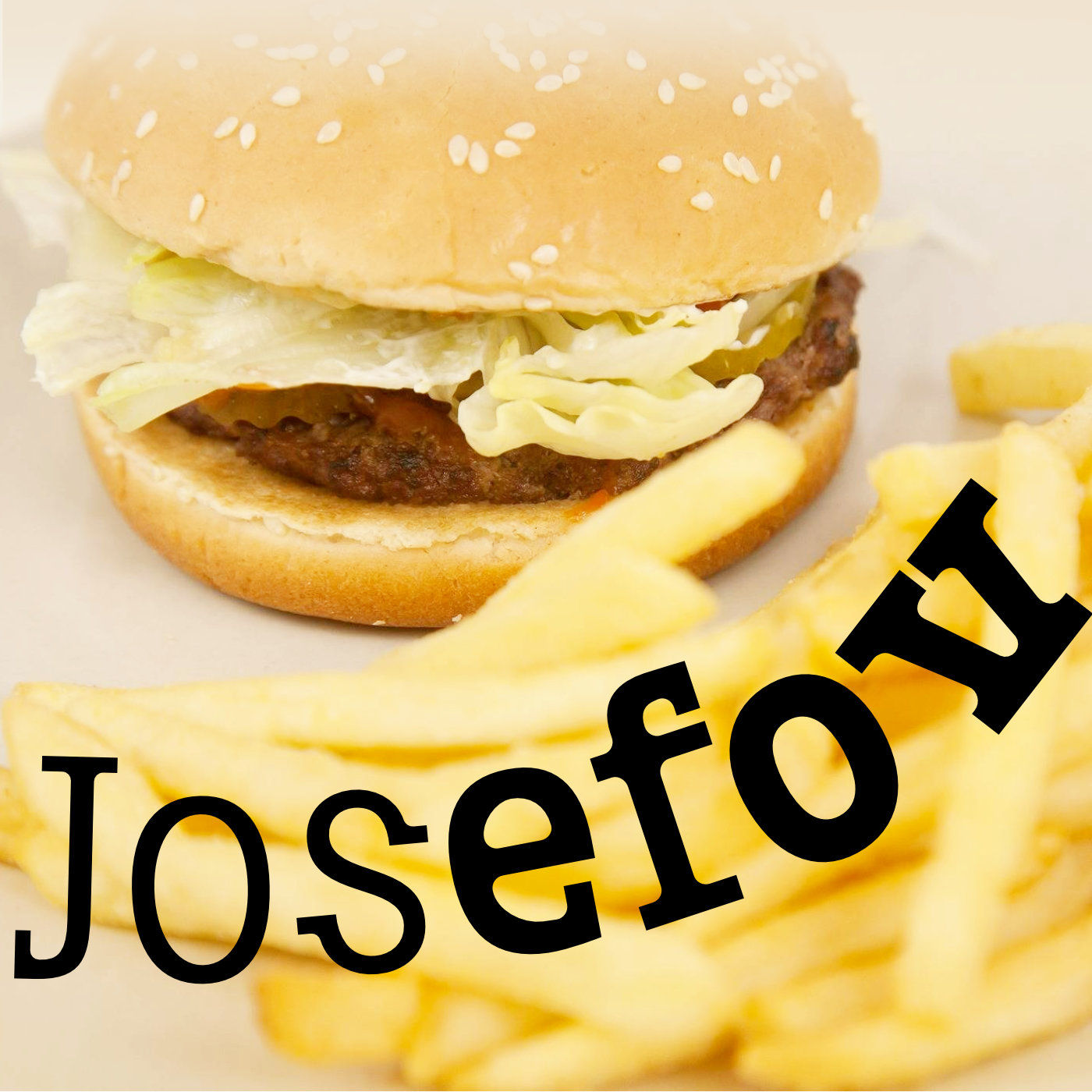
Une police étroite et moderne avec des empattements accentués
Comme son nom l'indique, Josefov est directement dérivée de la police sans serif >> « Josef ».
C'est de là que vient le rapport inhabituel pour les polices de caractères romaines entre la hauteur x élevée et les longueurs supérieures et inférieures très courtes. L'idée de base était de créer une police avec des empattements arrondis, dans le style de la bonne vieille Clarendon, mais sans trop y faire penser. En outre, le principe de forme des empattements arrondis est appliqué dans la mesure du possible, par exemple aux endroits où les tracés individuels des lettres se fondent les uns dans les autres.
Le Josefov semble très technique, très construit (ce qu'il est effectivement).
Pour atténuer l'impression de rigueur, les empattements sont placés à certains endroits, contrairement à la tradition, comme pour les majuscules A, C, G, K, M, V, W et les noms communs a, b, d, h, i, j, k, l, s, t.
Historiquement, les empattements latéraux du s majuscule et du s minuscule ou du S et du C, G, sont sans précédent.
Les empattements bilatéraux sur les pleins de b, d, h, k, l apparaissent en revanche au tout début de l'ère moderne dans les toutes premières polices Antiqua de Sweynheim et Pannartz (vers 1480) et autres. Les empattements bilatéraux de A, M, V, W étaient également très courants dans les premières décennies de l'imprimerie.